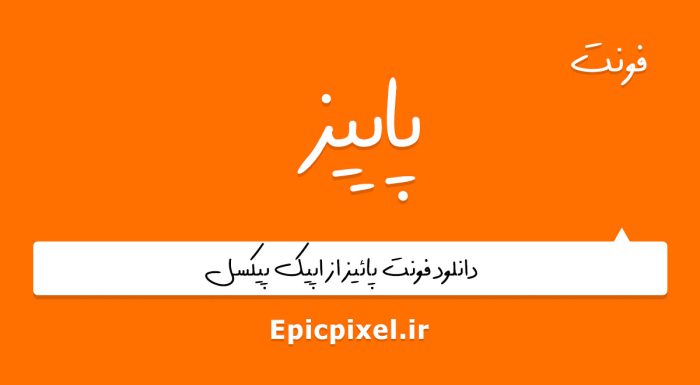
3 فونت پاییز فارسی
فونت پاییز یک حس عمیق از دوستی رو بین شما و مخاطبتون برقرار میکنه و باعث میشه بتونین صمیمیت رو توی متن هاتون قراربدین تا دلنوشته هایی که با این فونت میذارین دل هاتون رو بیشتر به هم نزدیک کنه